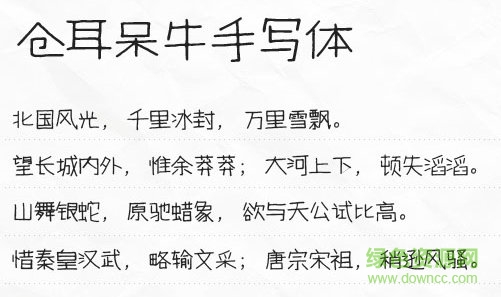
呆牛手寫(xiě)字體是蒼耳家族推出的一款手寫(xiě)字體,該字體干凈明了,給人字跡清爽分明的端正秀麗體驗(yàn),讓你的文字閱讀性更佳,快來(lái)綠色資源網(wǎng)試試吧!
呆呆萌萌,稍顯笨拙但又透著一股可愛(ài),直來(lái)直去從不拐彎抹角,在這個(gè)復(fù)雜的世界里保存著一份童真!